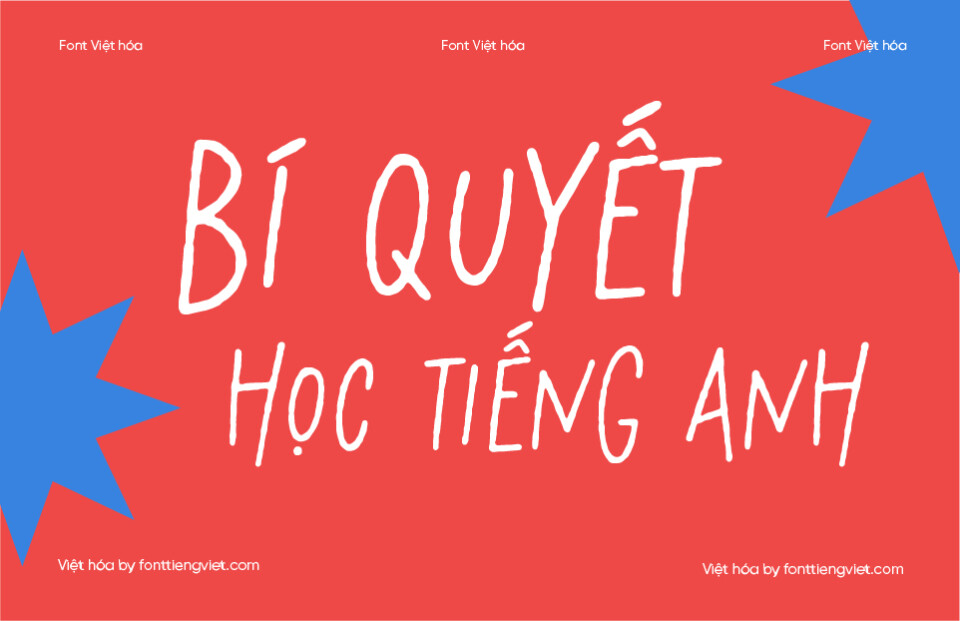
Font 1FTV English Speakers
Font 1FTV English Speakers mang đến một sự pha trộn tinh tế giữa tính thẩm mỹ và tính ứng dụng. Font 1FTV English Speakers thuộc bộ sưu tập font chữ viết tay với thiết kế tinh giản, thanh lịch, đã trở thành lựa chọn lý tưởng cho người học tiếng Anh như soạn thảo văn bản, thiết kế bài giảng và làm việc với tài liệu học thuật. Điểm nổi bật của Font 1FTV English Speakers chính là sự dễ đọc và dễ nhìn, giúp tăng tính mạch lạc và truyền tải thông điệp một cách hiệu quả. Các nét chữ cân đối, đầy đủ nhưng không rườm rã, tạo nên sự thanh lịch, trang nhã cho mọi văn bản.